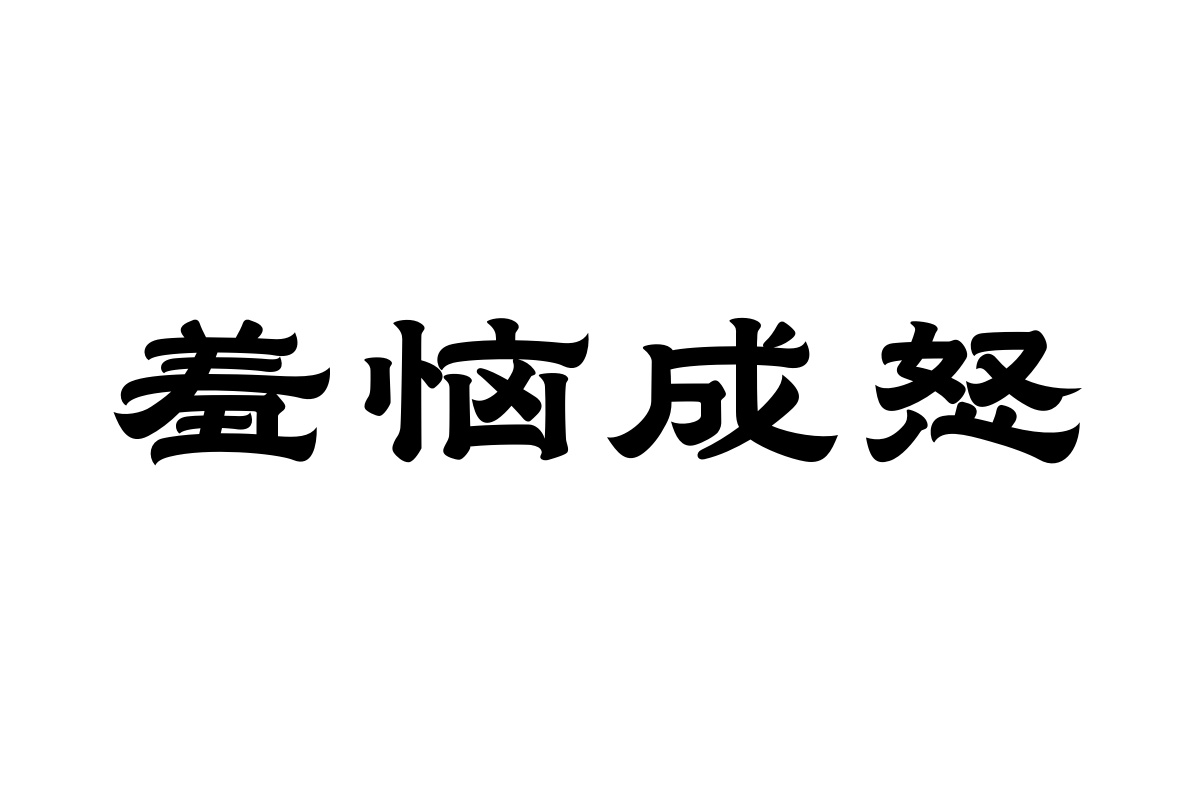
造字工房乘歌隶是一款由造字工房公司开发的中文字体,具有独特的艺术风格和视觉效果。这款字体采用了传统的隶书结构,结合了现代设计理念,使得文字更加简洁、易读。
乘歌隶字体的特点在于其流畅的线条和独特的字形设计,使得文字呈现出一种优雅而富有艺术感的效果。这款字体适用于各种需要展示文字的场合,如书籍、杂志、广告、网页等。
此外,乘歌隶字体还具有一定的可扩展性,可以通过调整笔画粗细、间距等参数来适应不同的应用场景。这使得用户可以根据自己的需求和喜好,自由地定制字体样式,满足个性化的需求。